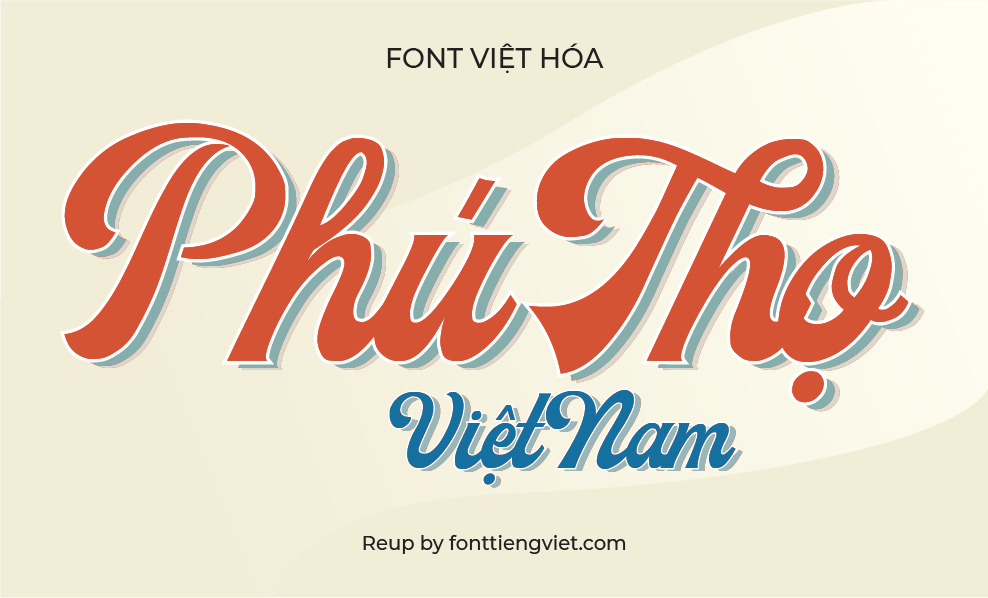
Tải Ngay Font việt hóa MJ Milestone ( Font vintage retro ) Đẹp Mắt Cho Thiết Kế
Chào mừng bạn đến với thế giới sáng tạo, nơi những bộ Font Chữ chất lượng giúp biến ý tưởng thành hiện thực. Trong bài viết này, chúng tôi xin giới thiệu bộ Font việt hóa MJ Milestone ( Font vintage retro ), một lựa chọn hoàn hảo cho những ai yêu thích phong cách hoài cổ. Đây là công cụ hỗ trợ đắc lực giúp các bạn học sinh và giáo viên tạo ra những bài thuyết trình hay ấn phẩm thiết kế ấn tượng, mang đậm dấu ấn thời gian nhưng vẫn giữ được nét hiện đại, tinh tế.
Khám phá đặc điểm của Font việt hóa MJ Milestone ( Font vintage retro )
MJ Milestone là một bộ font sở hữu đường nét mạnh mẽ, dứt khoát nhưng không kém phần mềm mại nhờ những đường cong đặc trưng của phong cách Retro. Khi được việt hóa, bộ font này đã tối ưu hóa toàn bộ các dấu câu tiếng Việt, giúp người dùng không còn lo lắng về lỗi hiển thị khi soạn thảo văn bản. Điểm nhấn của font chính là khả năng gợi nhớ về những tấm biển quảng cáo thập niên cũ, mang lại cảm giác ấm cúng và đầy tính nghệ thuật cho mọi khung hình.
Ứng dụng đa dạng trong học tập và sáng tạo
Với Font việt hóa MJ Milestone ( Font vintage retro ), bạn có thể dễ dàng thiết kế bìa báo tường, thiệp mời, hay các poster sự kiện trường học. Cấu trúc chữ rõ ràng giúp nội dung dễ đọc ngay cả khi nhìn từ xa. Ngoài ra, font còn cực kỳ phù hợp cho các dự án làm video kỷ yếu hoặc trang trí ảnh cá nhân theo hướng cổ điển. Sự kết hợp giữa màu sắc trầm ấm và kiểu chữ MJ Milestone sẽ tạo nên một tổng thể vô cùng hài hòa.